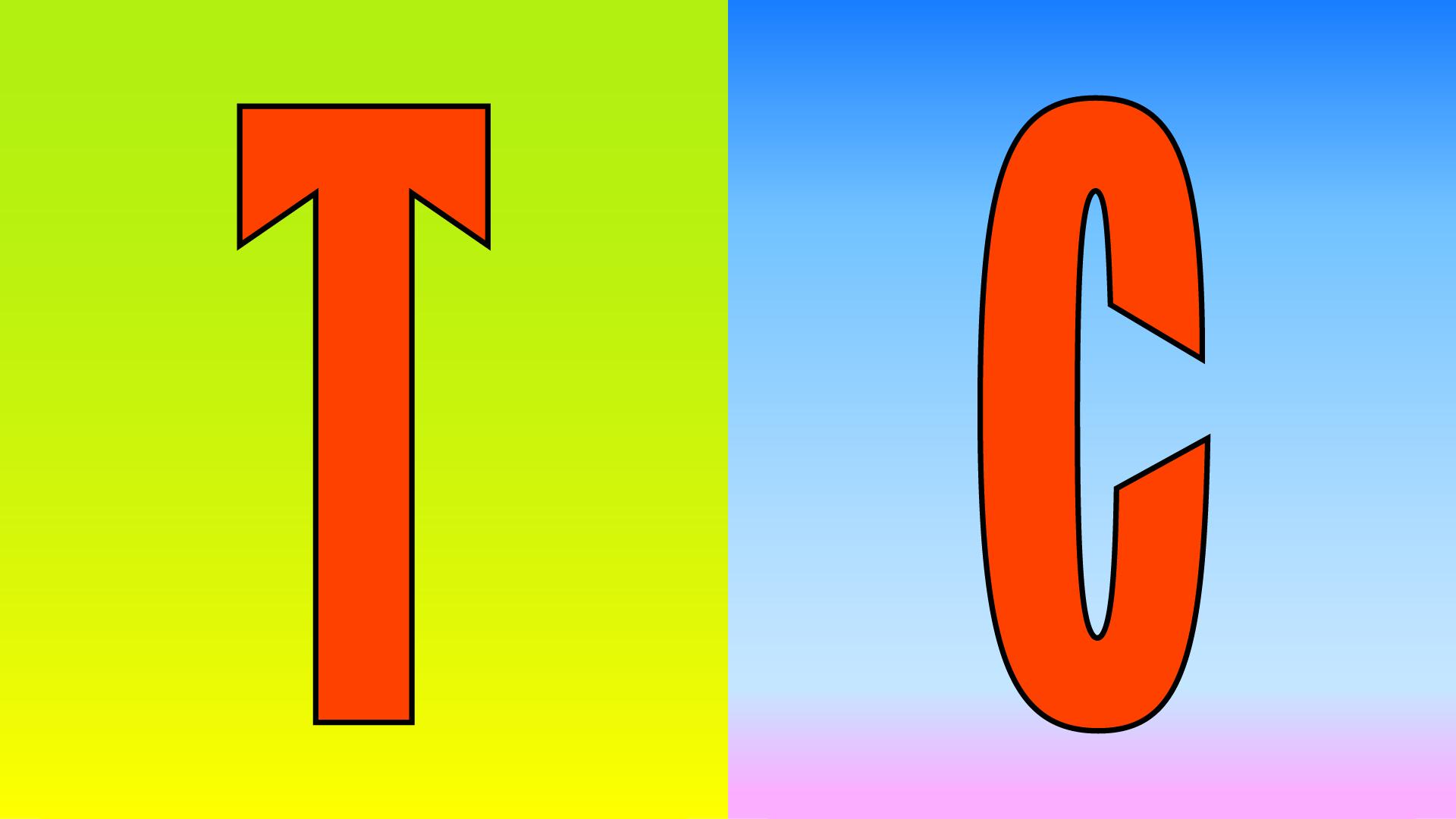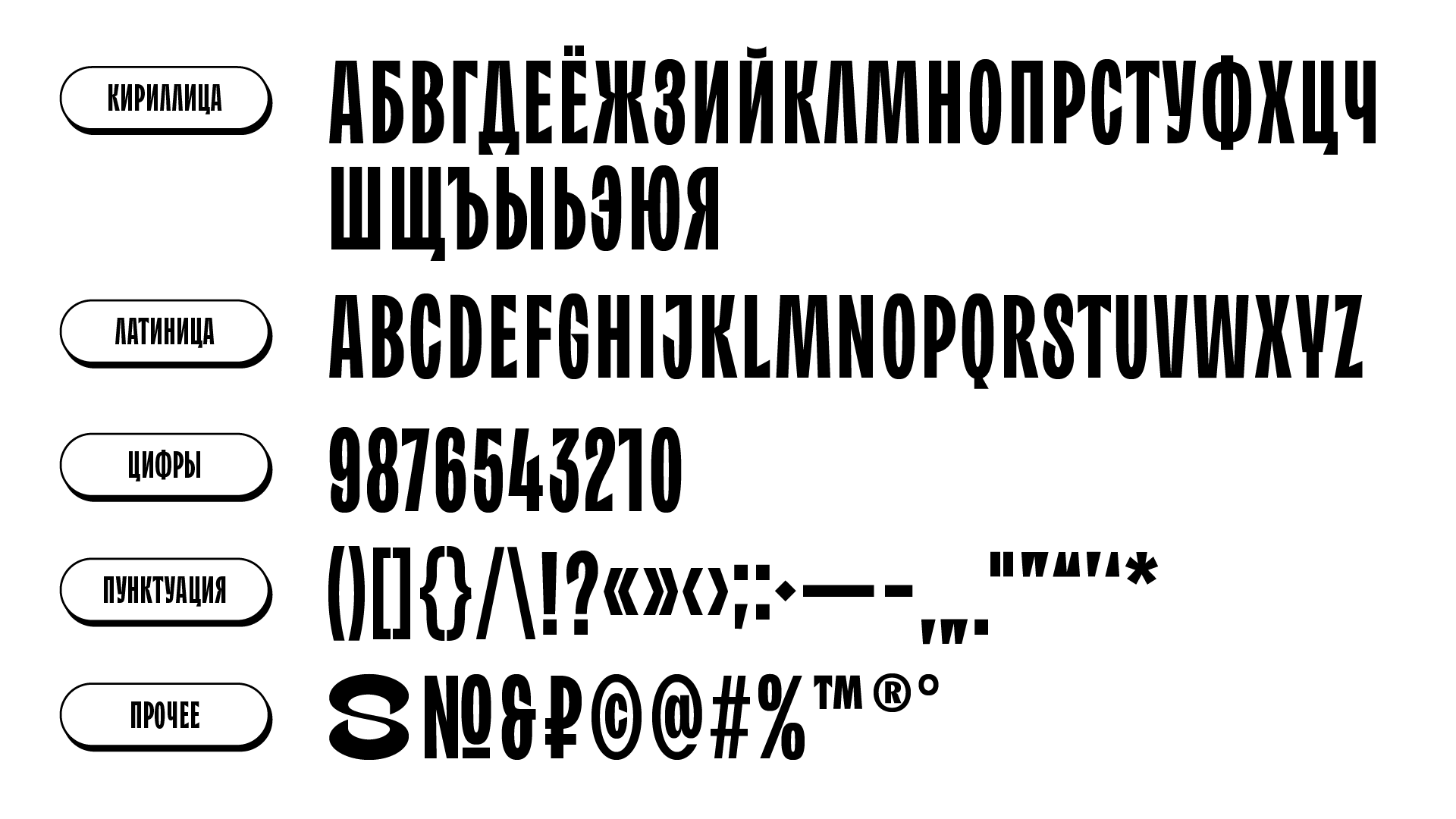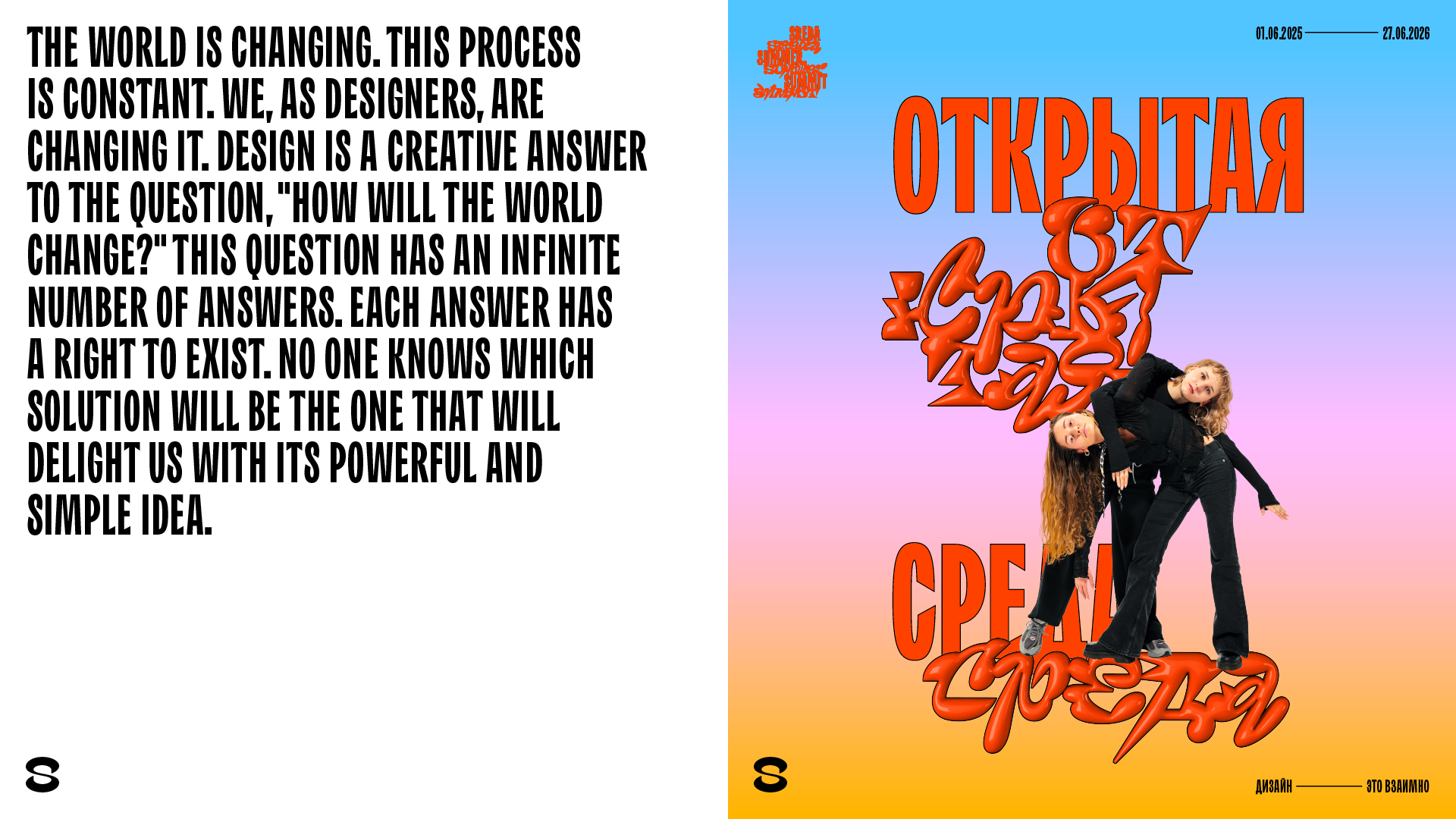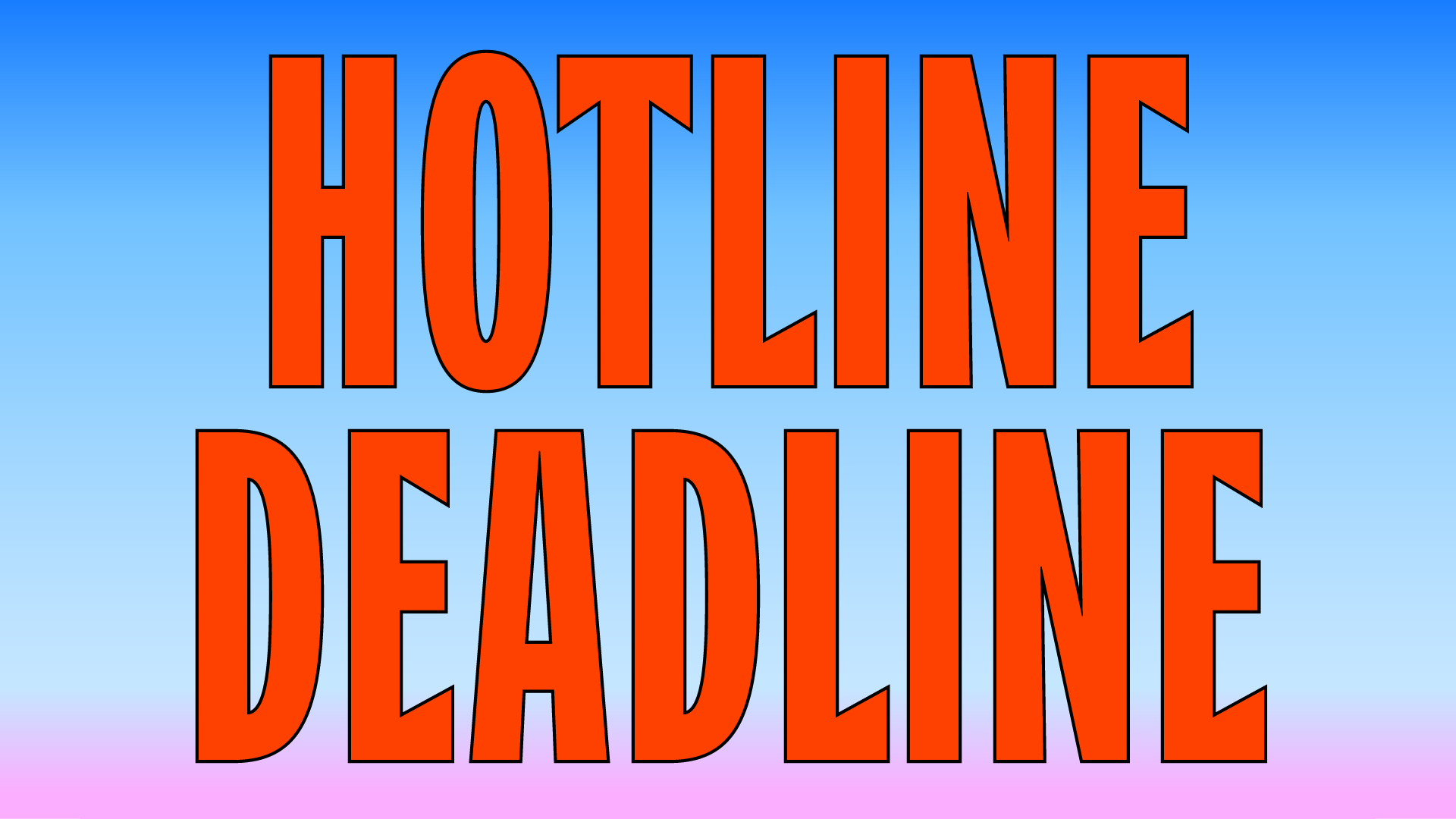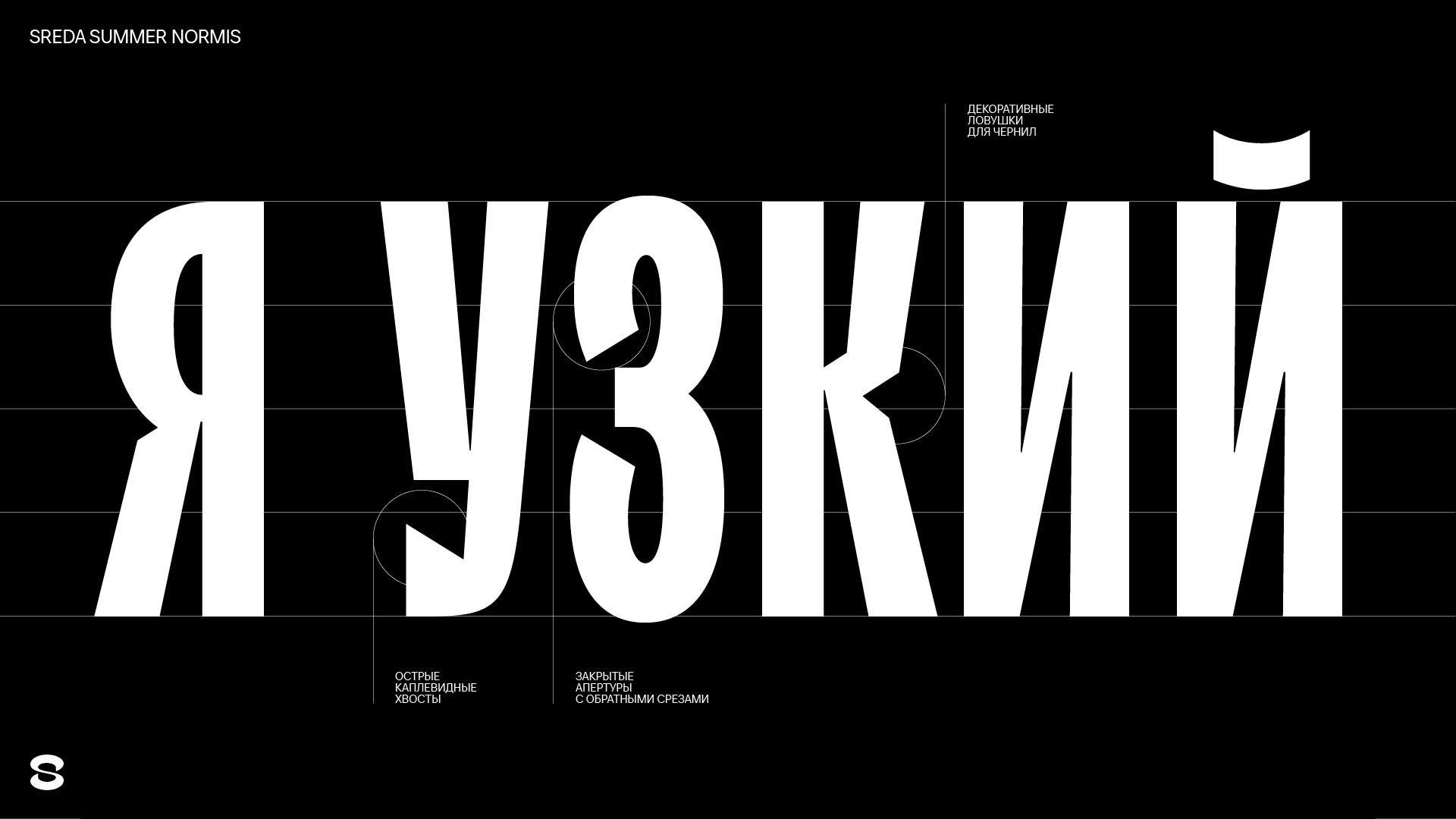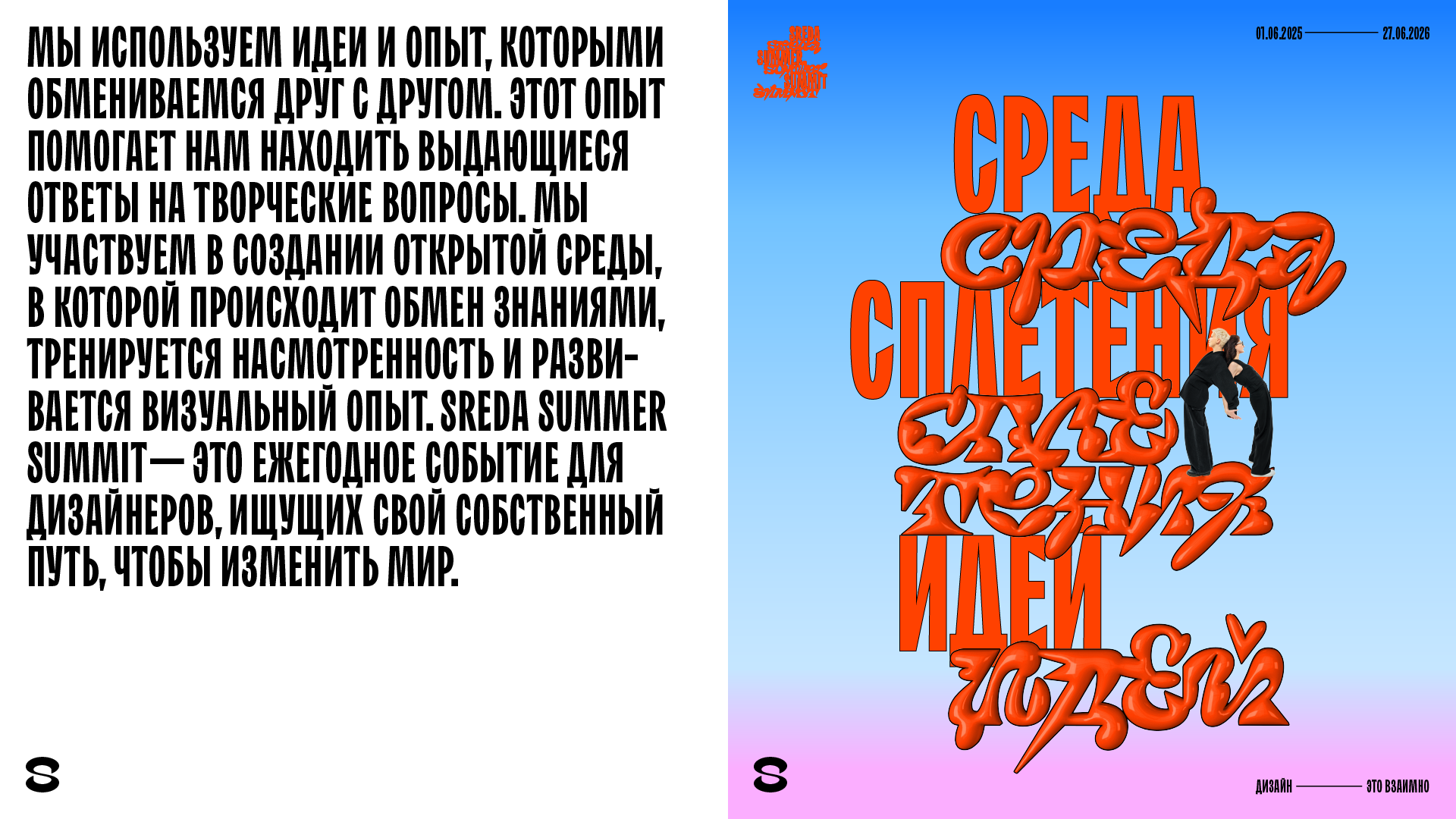
Sreda Summer Normis
Sreda Summer Normis — один из двух фирменных шрифтов, разработанных для фестиваля Sreda Summer Summit.
Узкий, плотный и колючий акцидентный гротеск. Обилие остроконечных элементов — его главная особенность. Закрытые круглые знаки шрифта обладают достаточно закрытой апертурой, но отличаются от привычных закрытых гротесков обращёнными вовнутрь наклонными срезами штрихов. Эти срезы поддерживаются треугольными терминалами, скошенными выносными элементами кириллических знаков и декоративными ловушками для краски. Тонкие соединения в знаках с наклонными штрихами также участвуют в усилении характера. Остроконечность шрифта уравновешивают приплюснутые овалы и полуовалы, которые делают шрифт дружелюбным.
Обилие декоративных элементов не мешает шрифту быть удобочитаемым в крупном и среднем кегле. Таким образом, шрифт выражает противоречивый дух сообщества дизайнеров, внутри которого напряжённая конкуренция соседствует с дружбой и сотрудничеством.